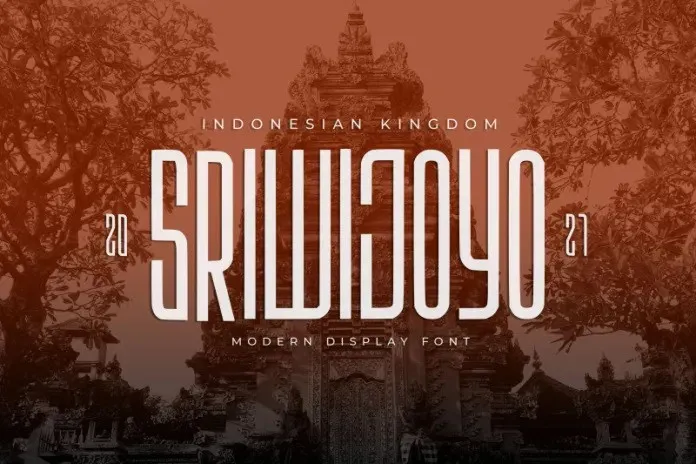
Sriwijoyo Font – Fonte Grátis
Sriwijoyo Font
A fonte Sriwijoyo é inspirada em selos antigos e cartões-postais retro que remetem à era das badges antigas. Desenvolvida para designers amantes dos estilos clássicos e futuristas, ela oferece uma gama de opções únicas para diversos tipos de projetos visuais. Com seu uso exclusivo de letras maiúsculas e suporte multilinguagem, a fonte apresenta alternativas para signos de pontuação, números e caracteres especiais. Ideal tanto para slogans modernas quanto para o design de logotipos, vlogs e banners web, ela também se destaca perfeitamente em promoções de música, restaurantes ou cafés. Com seu estilo único, a Sriwijoyo está aqui para ajudá-lo a destacar sua marca ou criatividade no mundo digital moderno.